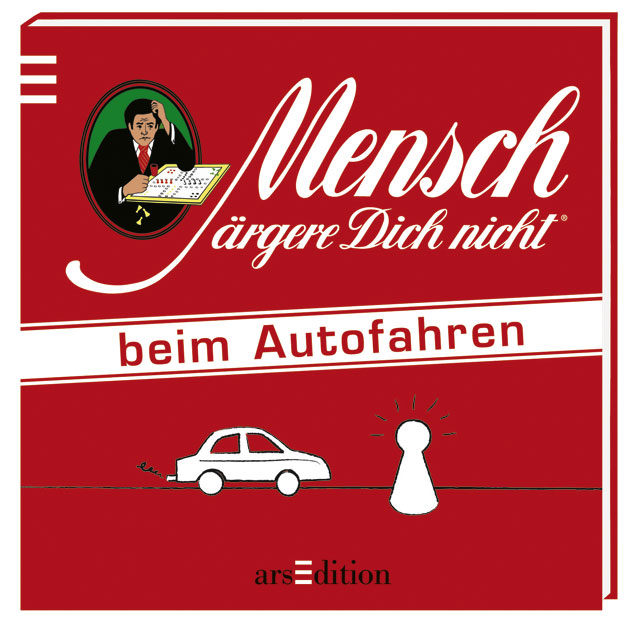
Welche Schrift ist die von "Mensch ärger dich nicht"?
Hallo! Wir müssen ganz schnell herausfinden welche Schrift bei dem Brettspiel "Mensch ärger dich nicht" verwendet wird! Und vielleicht weiß ja auch jemand, wie man an die Schrift kommen kann... vielen Dank.
Nein! Es ist nicht handgeschrieben! Es ist zwar von einer alten Verpackung, aber auf jeden Fall eine "echte" Schrift!
Scheint aber irgendwann mal überarbeitet worden zu sein, wie man an dem älteren Bild hier sieht: